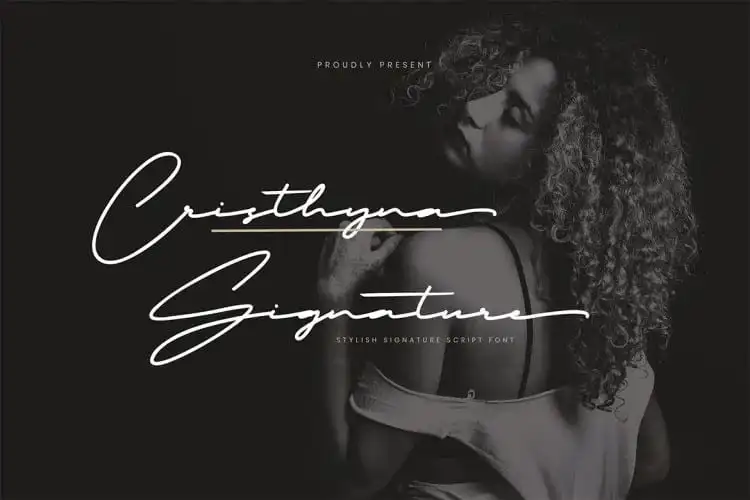
Cristhyna Signature Script Font – Download Grátis
A Cristhyna Signature Script Font é uma elegante fórmula de letra escrita a mão que captura o espírito do autêntico e sofisticado. Inspirada no estilo livre de letras, esta fonte traz um toque natural e refinado, perfeitamente adequada para criar assinaturas luxuosas e inovadoras. Criação do designer Namara Creative Studio, a Cristhyna é projetada com o objetivo de reproduzir a elegância das letras escritas à mão, oferecendo uma alternativa sofisticada à letra cursiva digitalizada. Esta fórmula de fonte é perfeita para diversidade de usos, desde assinaturas corporativas e embalagens cosméticas até invocações de casamento e capas de revistas. Suas linhas fluidas e seu design elegante a tornam uma excelente escolha para qualquer projeto que busca um toque autêntico e sofisticado. A Cristhyna é um recurso indispensável para designers, especialmente aqueles buscando adicionar um toque de singularidade a seus trabalhos. Aproveite o charme da Cristhyna para destacar sua marca ou transformar qualquer projeto em uma obra-prima visual. Esta fonte é perfeita para quem busca a elegância e sofisticação que só a escrita à mão pode fornecer, oferecendo aos designers uma maneira única de expressar estilo e personalidade no design gráfico.